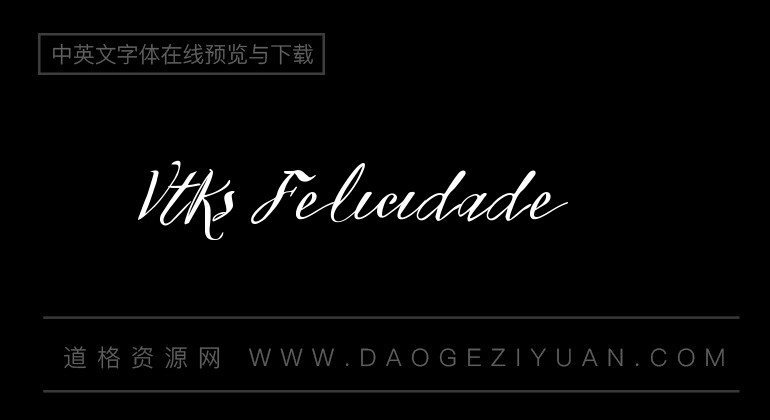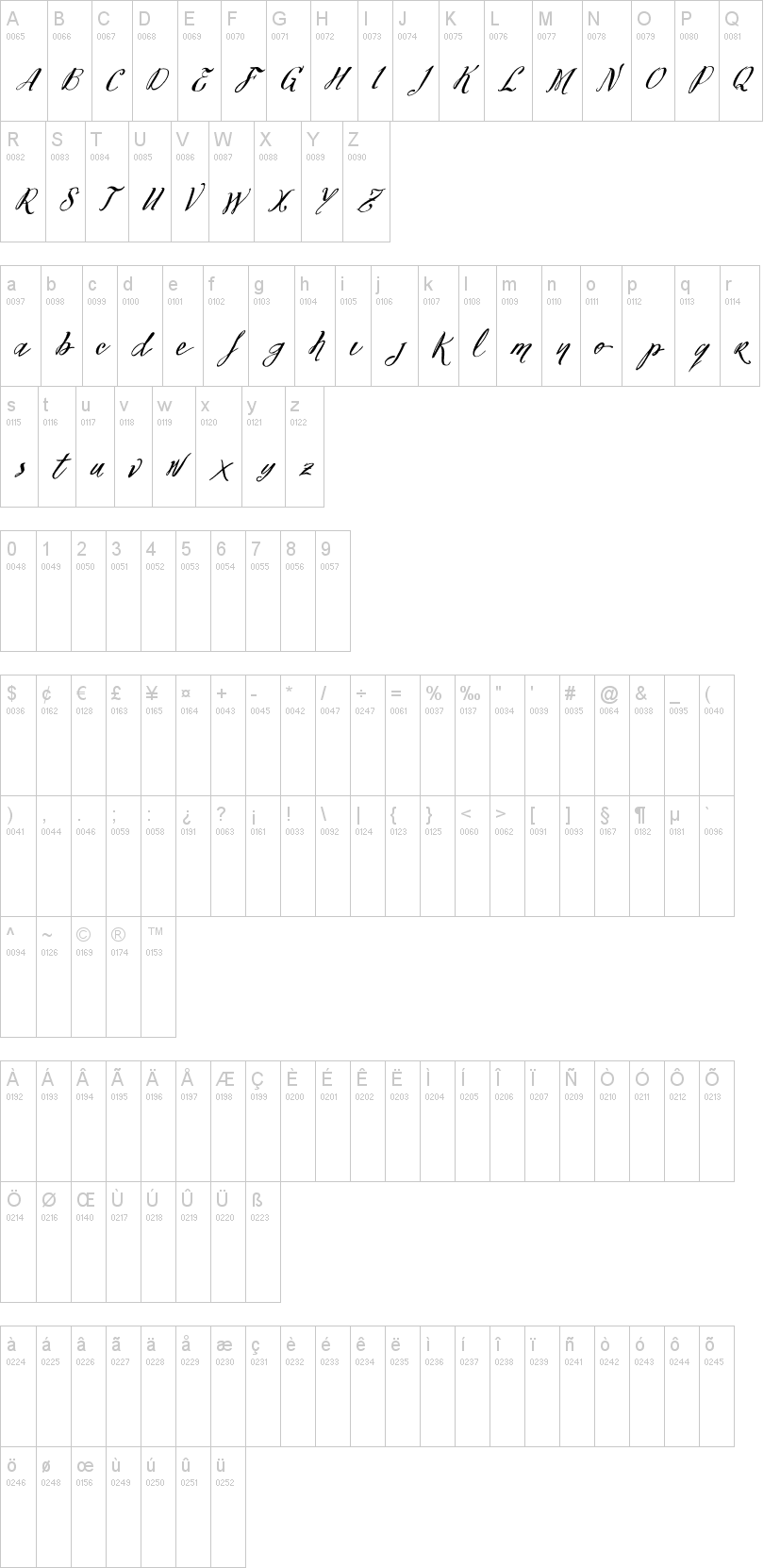
Vtks Felicidade 2016 字体是一款具有极具特色的手写体字体,它采用复古的设计风格,具有浓浓的艺术气息,可以很好地表达出温暖、欢乐、激情和快乐的情绪。字体特点是粗犷、清晰、明亮,拥有明显的节奏感,可以为您的文字添加一种独特的韵律感,使您的文字更加有趣而生动。它适用于各种广告、书籍、海报、婚礼邀请函等等,可以帮助您创造出独特的文字效果。内容介绍
Vtks Felicidade 2016是一款非常不错的手写艺术字体,具有很好的视觉感,适合于文化类的宣传设计、商业类品牌的广告和产品包装设计以及个性化文字排版等较多场景。